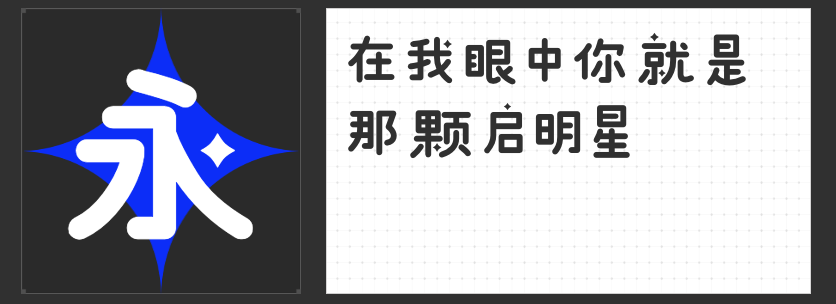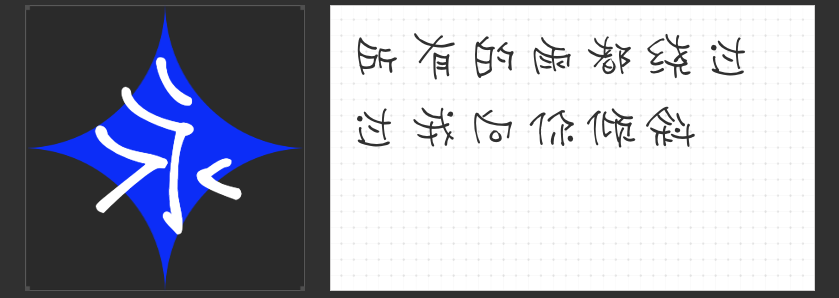
短视频字体新宠:四款创意无限的字库字体推荐
在短视频制作中,字体的选择往往能够决定视频的整体风格和氛围。今天,我们为大家推荐四款专为短视频设计的创意字库字体,它们各具特色,能够满足不同风格和场景的需求。
一、励字磅礴简 超黑
这款字体融合了斜体与正体的设计,左侧倾斜的笔画为整体稳重大气的字形增添了一丝灵动。右侧的垂直设计则支撑起整个架构,营造出“气势磅礴,万壑争流”的视觉效果。在短视频中,励字磅礴简 超黑能够瞬间抓住观众的眼球,无论是用于标题还是字幕,都能让视频显得更加高端大气。
二、字恋狂嗨玩简
字恋狂嗨玩简以其粗壮的笔画和方块字形脱颖而出,像积木一样的设计给人一种笨拙可爱的感觉。这款字体非常适合用于活泼、欢快的短视频场景,如搞笑、娱乐等内容。它的独特风格能够让视频更加生动有趣,吸引观众的注意力。
小豆岛惠中谐趣简繁字体结构整体倾斜,通过正统书法笔画间架的解构,创造出一种重心倾斜的视觉感。这种设计充分体现出活泼谐趣的特点,非常适合用于二次元、旅行、鬼畜等风格的短视频。它能够为视频增添一份轻松愉悦的氛围,让观众在观看过程中感受到更多的乐趣。
四、高手兵克星耀体
高手兵克星耀体以其柔和圆润的笔画和独特的星星形状点笔画而备受瞩目。这款字体给人一种温暖而梦幻的感觉,非常适合用于温馨、浪漫或科幻风格的短视频。它的名称与字体设计完美匹配,能够营造出一种独特的视觉效果,让观众在观看过程中留下深刻的印象。
这四款字库字体各具特色,能够满足不同风格和场景的短视频制作需求。它们不仅能够提升视频的整体美感,还能让视频更加生动有趣,吸引更多观众的关注和喜爱。如果你正在寻找适合短视频的字体,不妨尝试一下这些创意无限的选择吧!